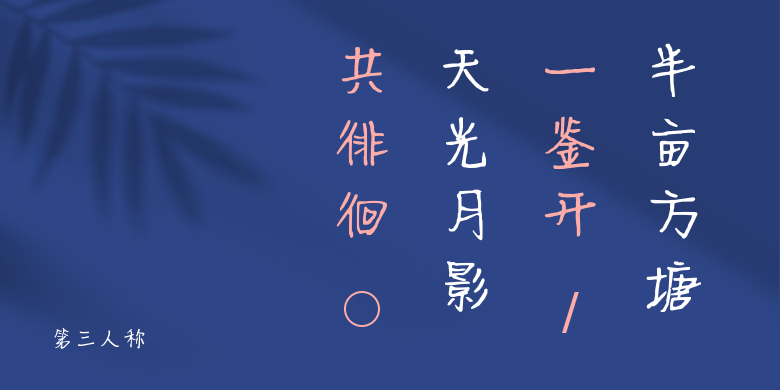
第三人称
第三人称,这款字体结构工整、笔画清晰,兼顾美观与易读性,适用于标题、正文、海报、包装、LOGO 等多种场景。字形优雅稳定,风格百搭耐看,适配日常排版与创意设计,让文字呈现更舒适、更具质感。第三人称一笔一画,皆是细节,以均衡的比例、流畅的线条打造舒适视觉体验,字形端正大气,风格简约现代。无论是商业设计、品牌宣传还是日常排版,都能轻松驾驭,让文字更有格调与力量。第三人称字体下载。